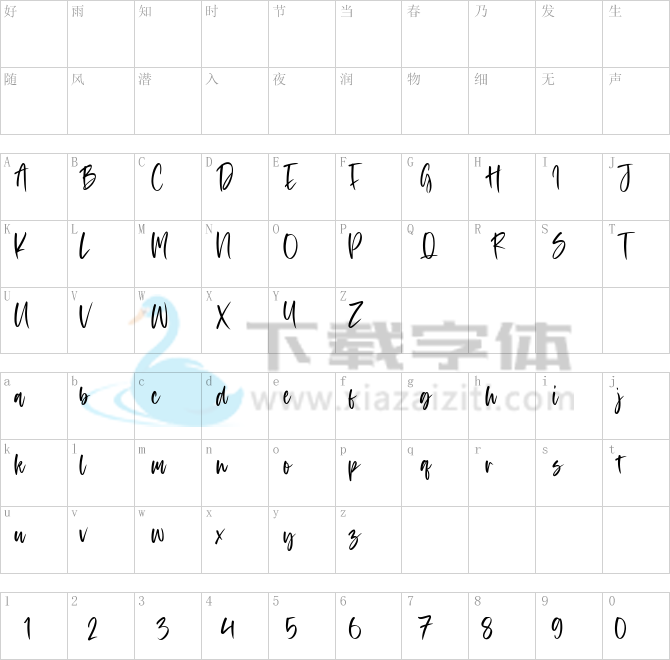
Acordian.otf字体下载,这款字体结构工整、笔画清晰,兼顾美观与易读性,适用于标题、正文、海报、包装、LOGO 等多种场景。字形优雅稳定,风格百搭耐看,适配日常排版与创意设计,让文字呈现更舒适、更具质感。Acordian.otf字体下载一笔一画,皆是细节,以均衡的比例、流畅的线条打造舒适视觉体验,字形端正大气,风格简约现代。无论是商业设计、品牌宣传还是日常排版,都能轻松驾驭,让文字更有格调与力量。Acordian.otf字体下载字体下载。